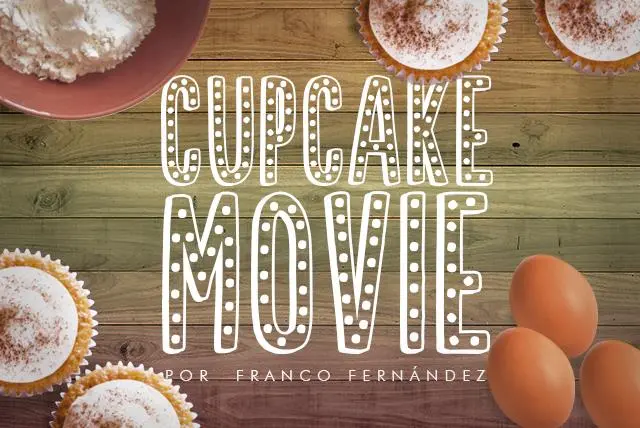
A fonte Cupcake Movie é uma criação criativa e única da designer franco-fernández, inspirada na sensação alegre e colorida dos doces cupcakes. Esta fonte Display é ideal para designers que buscam um elemento visual divertido e vibrante em suas criações de design gráfico e publicitário. Ideal tanto para nomes comerciais quanto para elementos visuais em projetos digitais, Cupcake Movie oferece uma série de tamanhos e pesos diferentes que garantem a legibilidade necessária enquanto mantêm sua essência colorida e animada. Suas formas leves e delicadas evocam imagens de doces cupcakes nas bordas do doce e açucarizados, mas também transmitem um espírito leve e vivaz capaz de tornar qualquer projeto mais atraente. A fonte está disponível em uma variedade de tamanhos e tonalidades que permitem ao designer adaptá-la à diversidade dos projetos gráficos, desde criações publicitárias até logotipos e design editorial. A Cupcake Movie é uma escolha perfeita para quem busca adicionar um toque alegre e único aos seus projetos digitais, sem comprometer a legibilidade ou a simplicidade de seu design. Com sua paleta vibrante de cores e forma única que evoca o encanto dos cupcakes, Cupcake Movie é uma fonte ideal tanto para aqueles iniciantes no design gráfico quanto para designers experientes procurando por algo novo. Através desta fonte, designers podem capturar a essência divertida e colorida da vida, adaptada de forma elegante para qualquer projeto.